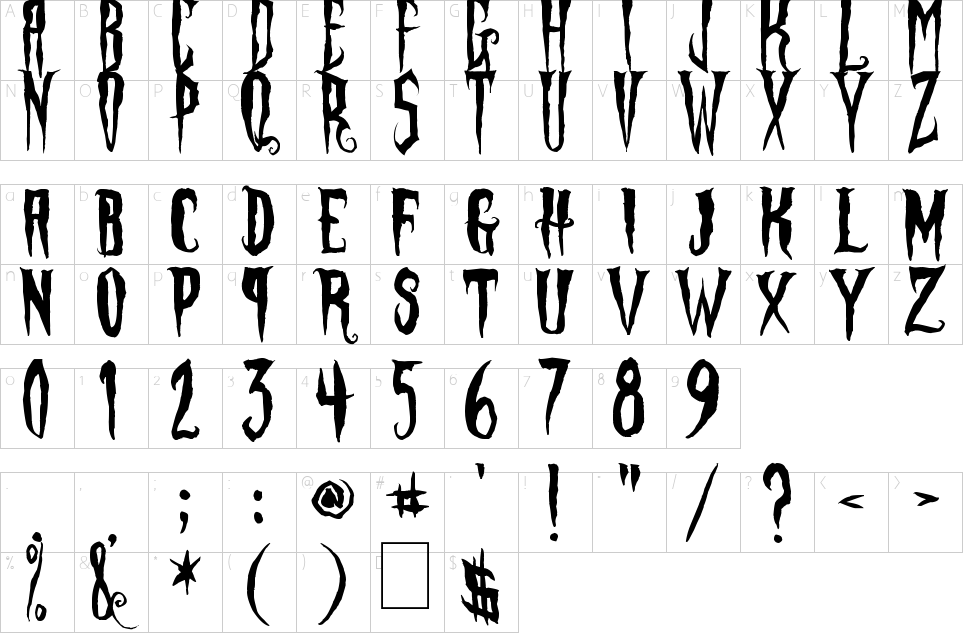
Descubra Phantom Fingers, uma fonte elegante e inovadora para seus projetos digitais. Desenvolvida pelo designer Sinister Fonts, esta fonte oferece um toque distinto e moderno que certamente enriquecerá sua arte digital. Se você está procurando uma opção clara e sofisticada para textos gráficos, Phantom Fingers é a escolha perfeita. Esta fonte tem sido baixada por mais de 6.000 vezes, uma indicação de sua popularidade e qualidade. Não deixe de adicionar Phantom Fingers ao seu arsenal de ferramentas de design; é uma escolha inconfundível para quem valoriza estética e funcionalidade em sua fonte gráfica.